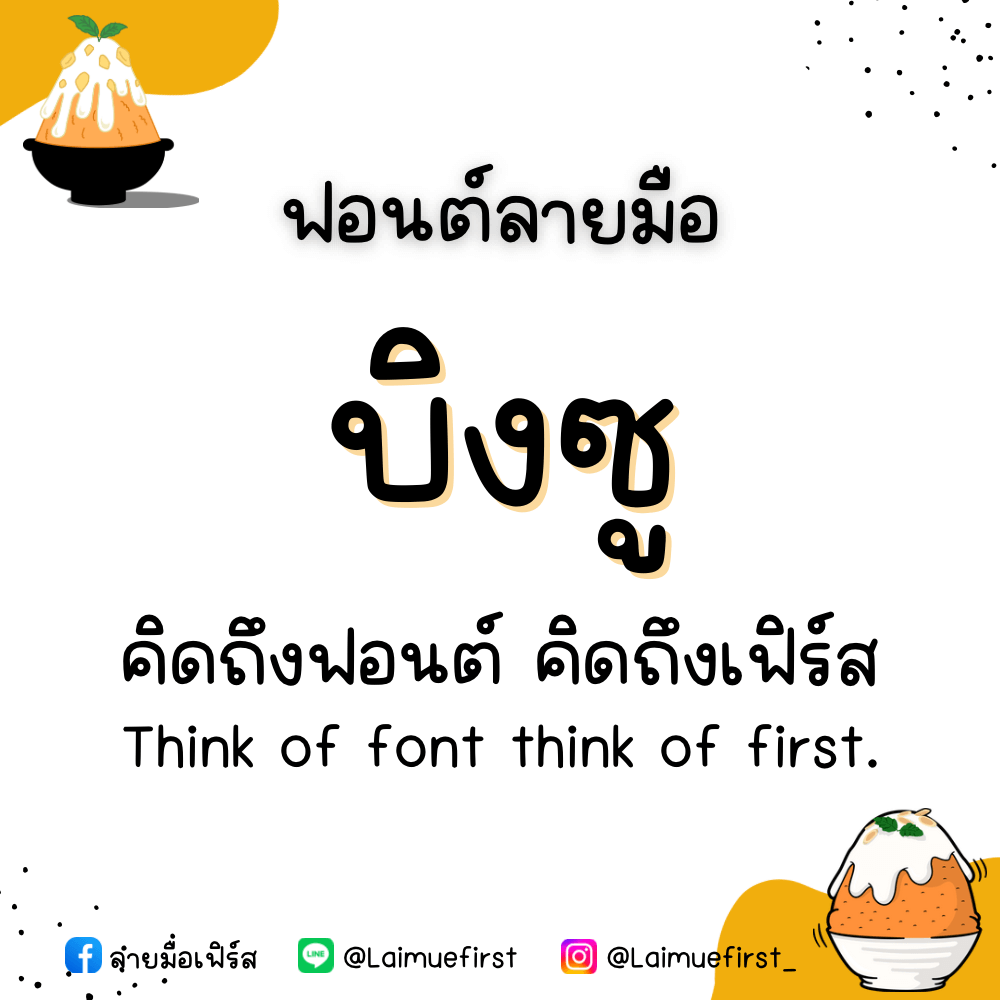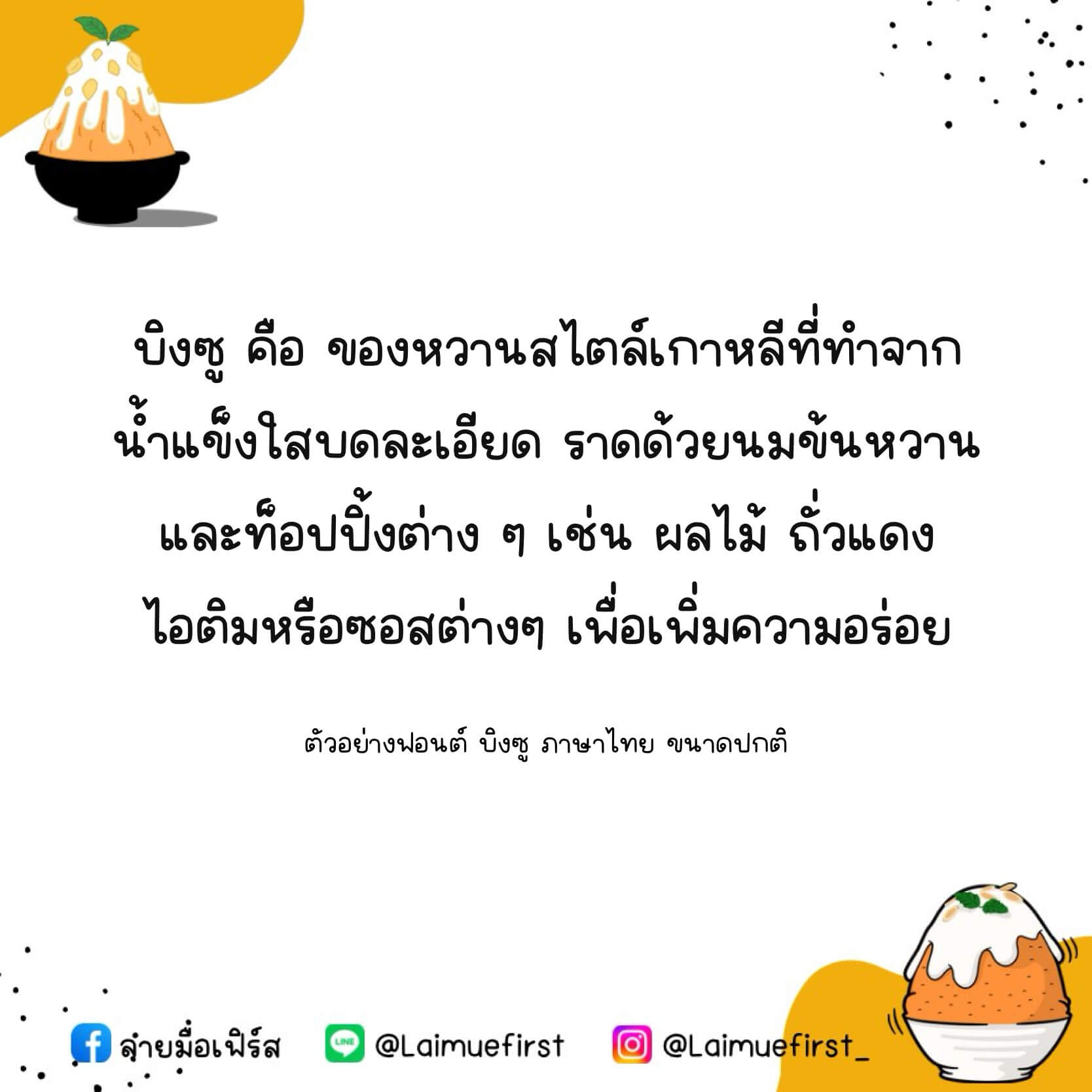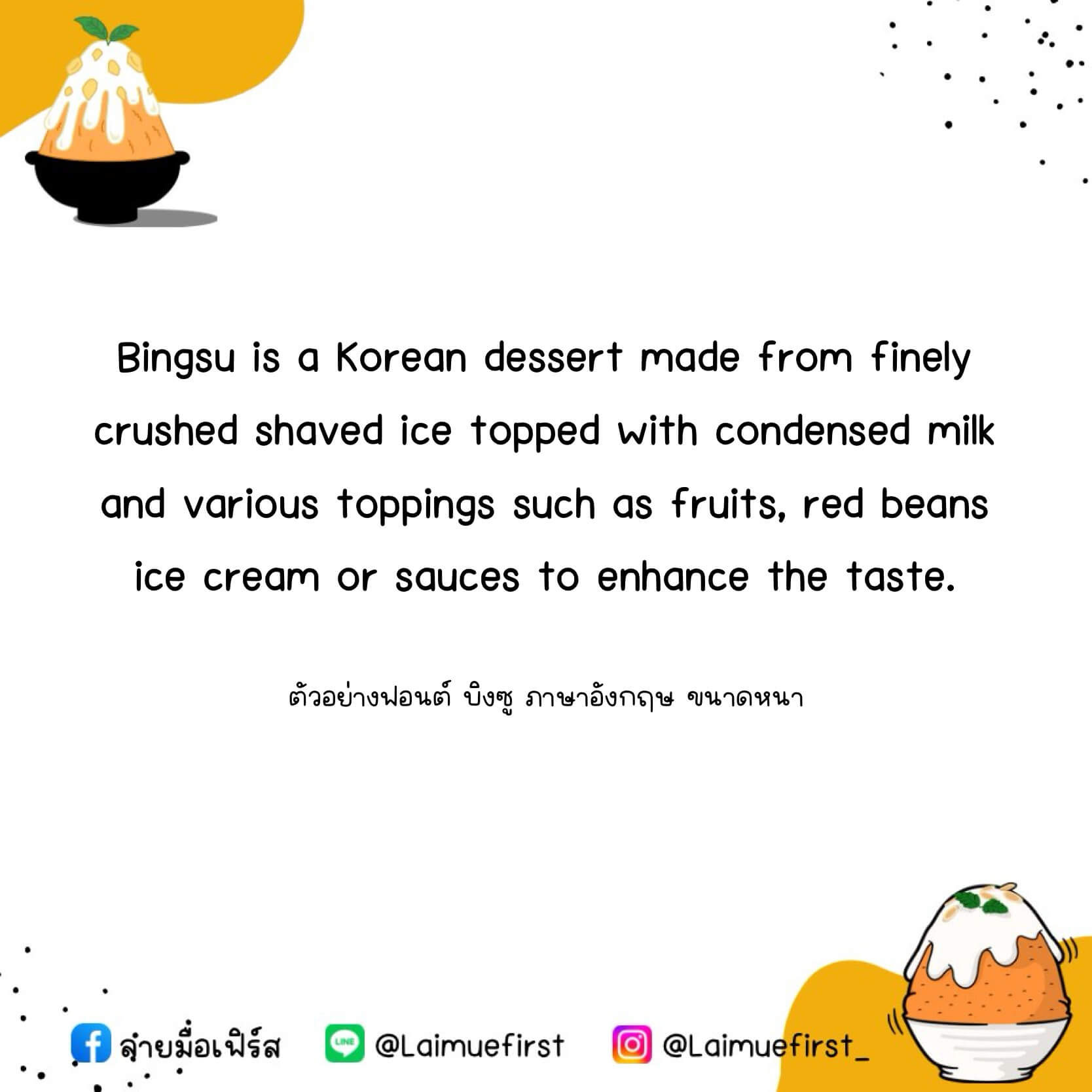
บิงซู (LMF Bingsu)
ฟอนต์ลายมือ บิงซู แจกฟรีสำหรับทดลองใช้งานแบบส่วนตัว เวอร์ชันทดลอง (Demo) ตัวอักษรจะมีขนาดหนา-บางไม่เท่ากัน ไฟล์นี้ไม่อนุญาตให้นำไปใช้เชิงพาณิชย์นะค้าบบบ